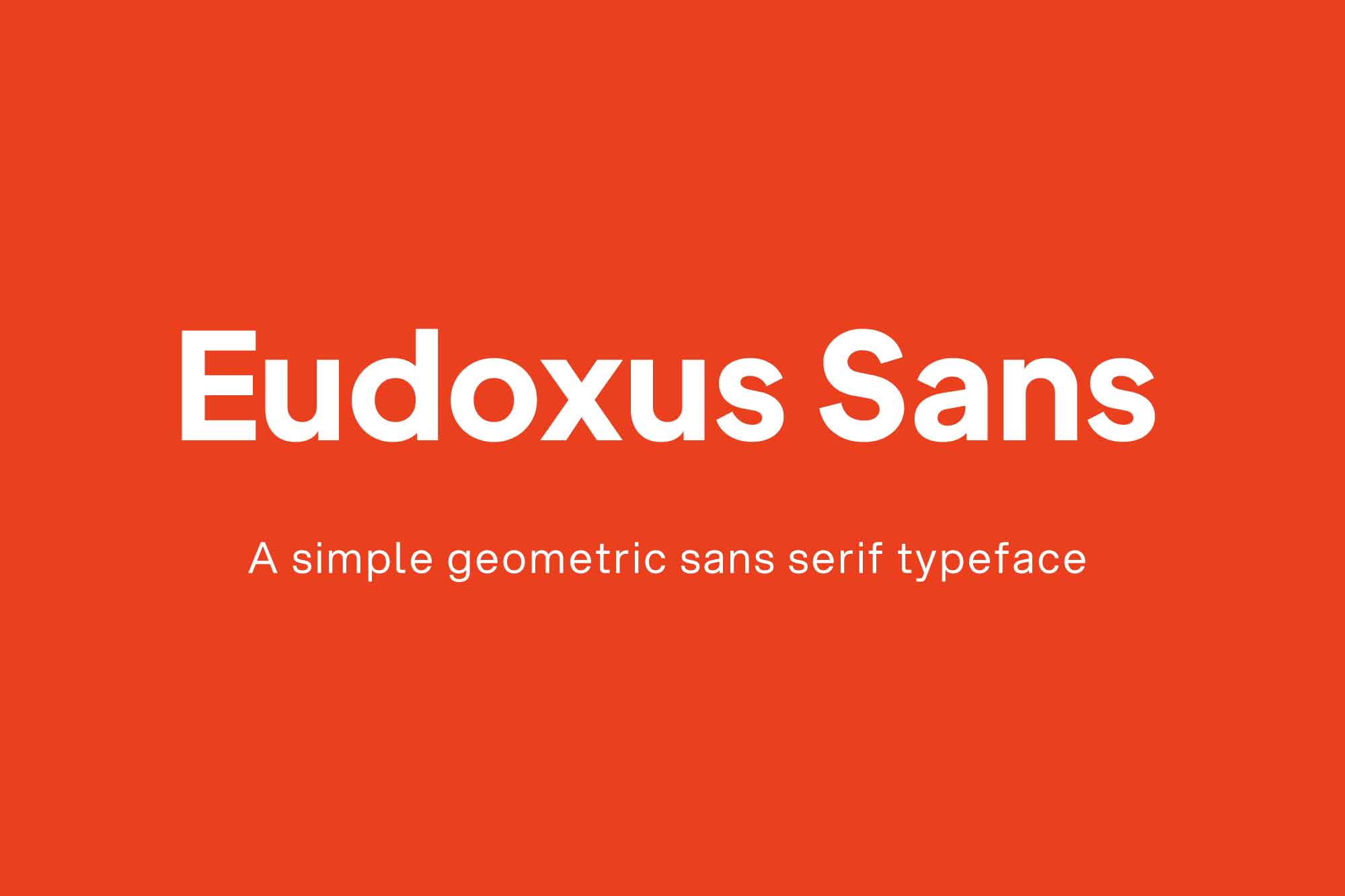
Eudoxus Sans Font
Eudoxus é uma fonte de tipo sans serif livre que traz uma construção geométrica simplificada, tornando-a perfeita para uso em diversas tarefas. Esta fonte é inspirada no matemático Eudoxus de Cnidus, um especialista em matemática e um dos matemáticos gregos mais talentosos de todos os tempos. Eudoxus é altamente legível e pode se tornar uma opção de escolha favorita para design gráfico e usos cotidianos em tipografia. Com seu design geométrico e sua simplicidade, Eudoxus é uma escolha inteligente para quem busca um estilo sóbrio e confiável. Seja você um profissional de design ou uma pessoa que simplesmente busca recursos gráficos de qualidade, Eudoxus é uma excelente opção para se tornar seu próximo recurso favorito.